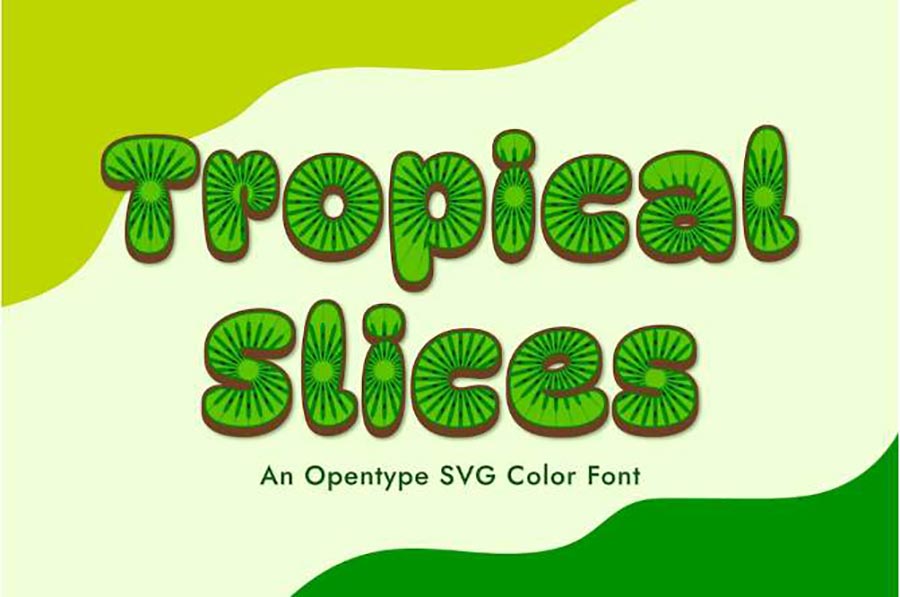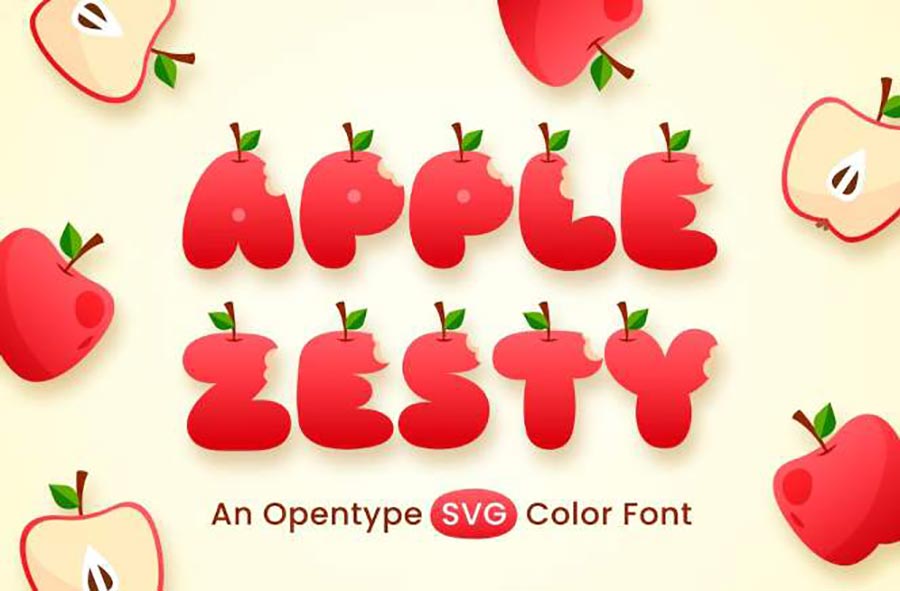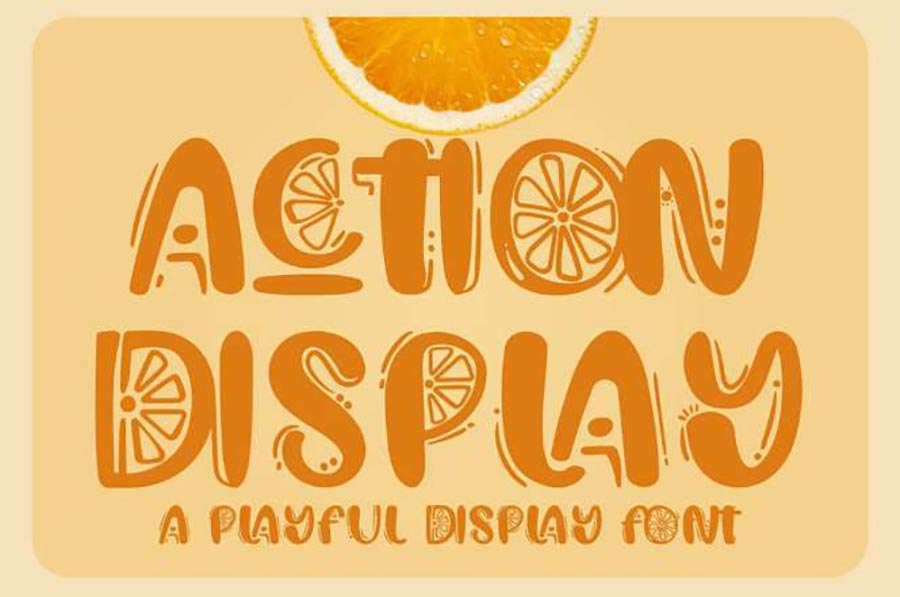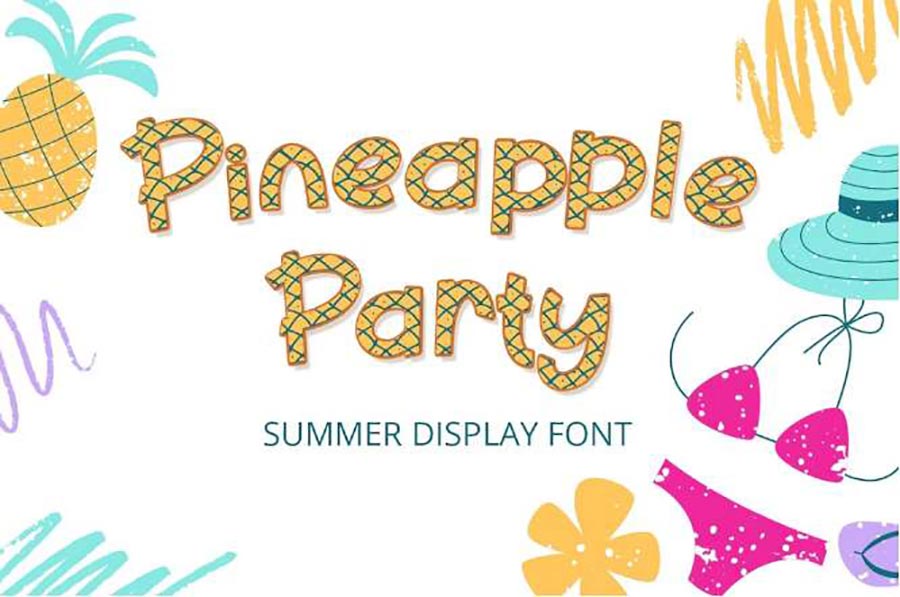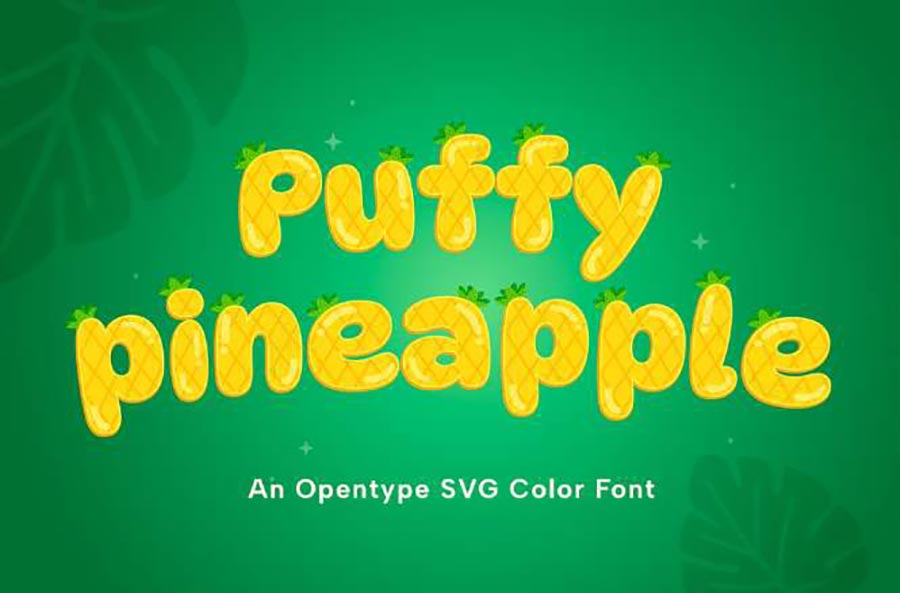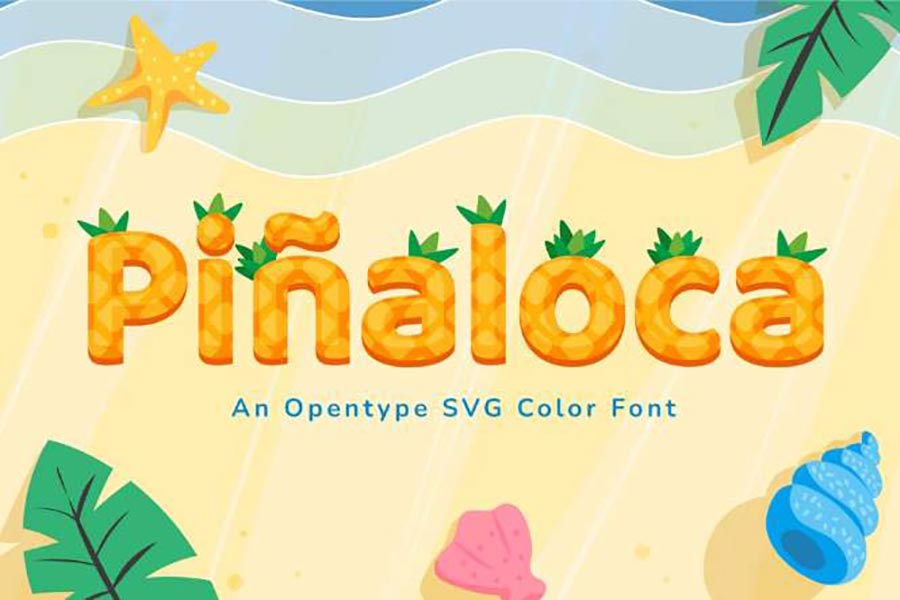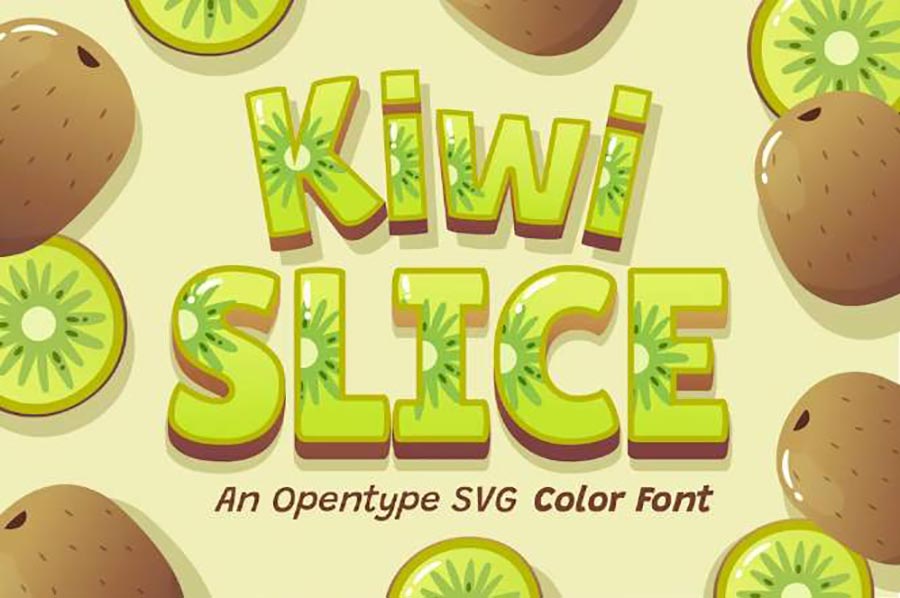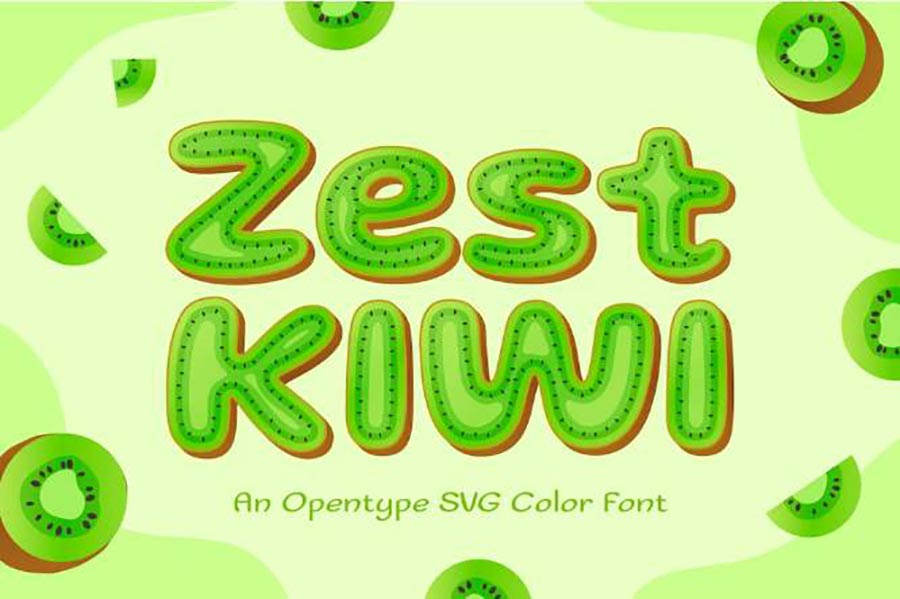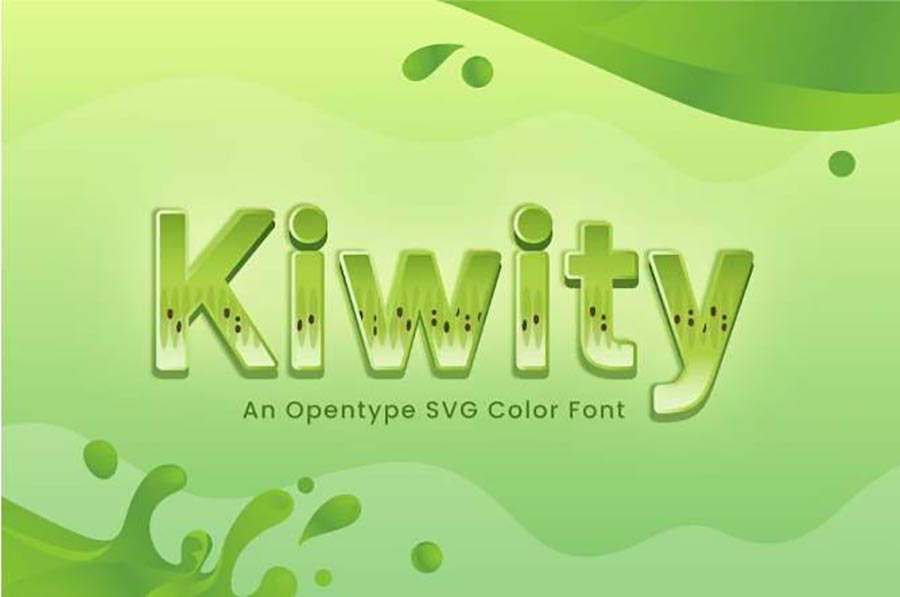
Bộ Fonts Chữ Trái Cây Nhiều Màu – Điểm Nhấn Sáng Tạo Trong Thiết Kế
Phong Cách Độc Đáo Và Đầy Màu Sắc
Bộ fonts chữ trái cây mang đến sự khác biệt với phong cách thiết kế đầy màu sắc, mô phỏng các loại trái cây như cam, dâu, kiwi, và nhiều loại khác. Mỗi font đều được tạo hình chi tiết, giúp truyền tải thông điệp tươi vui và sáng tạo.
Ứng Dụng Đa Dạng
Các font này phù hợp với nhiều loại dự án thiết kế như:
• Quảng cáo thực phẩm: Làm nổi bật sự tươi ngon của các sản phẩm.
• Poster sự kiện: Tạo không khí năng động và tràn đầy sức sống.
• Thiết kế logo: Mang lại vẻ ngoài độc đáo và khó quên.
Ưu Điểm Của Bộ Fonts Chữ Trái Cây Nhiều Màu
Chất Lượng Cao
Fonts chữ được thiết kế với độ phân giải cao, đảm bảo rõ nét và không bị vỡ hình khi phóng lớn.
Lưu Ý Khi Sử Dụng Fonts Chữ Trái Cây Nhiều Màu
Chọn Màu Nền Phù Hợp
Nên kết hợp fonts với các màu nền đơn giản để làm nổi bật họa tiết và chi tiết bên trong từng ký tự.
Tránh Lạm Dụng Fonts Trong Thiết Kế
Để giữ sự chuyên nghiệp, chỉ sử dụng fonts này cho các tiêu đề hoặc điểm nhấn thay vì áp dụng toàn bộ cho nội dung.
Kiểm Tra Kích Thước Trước Khi In
Trước khi đưa vào in ấn, cần kiểm tra độ rõ nét và kích thước để đảm bảo chất lượng thiết kế.